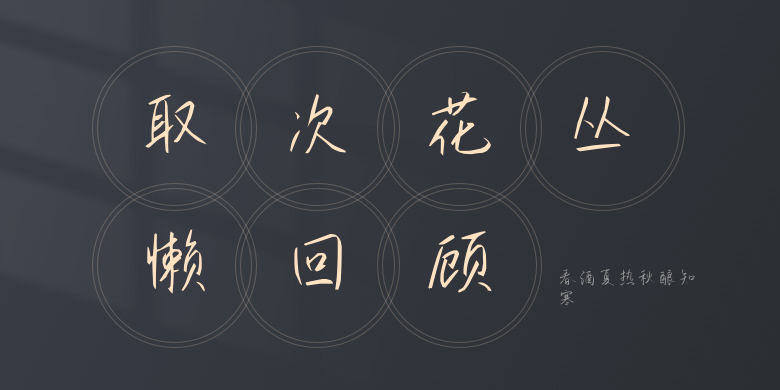
春酒夏热秋酿知寒
春酒夏热秋酿知寒,这款字体结构工整、笔画清晰,兼顾美观与易读性,适用于标题、正文、海报、包装、LOGO 等多种场景。字形优雅稳定,风格百搭耐看,适配日常排版与创意设计,让文字呈现更舒适、更具质感。春酒夏热秋酿知寒一笔一画,皆是细节,以均衡的比例、流畅的线条打造舒适视觉体验,字形端正大气,风格简约现代。无论是商业设计、品牌宣传还是日常排版,都能轻松驾驭,让文字更有格调与力量。春酒夏热秋酿知寒字体下载。